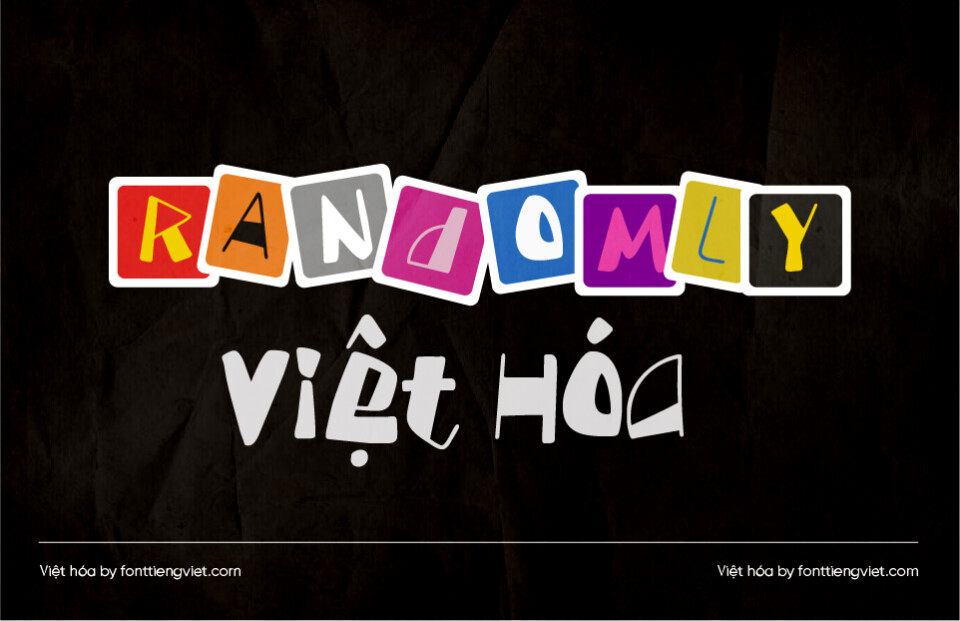
Font Việt hóa 1FTV Randomly Regular
Trong thế giới đồ họa hiện đại, việc lựa chọn một bộ Font Miễn Phí chất lượng đóng vai trò quyết định đến tính thẩm mỹ của sản phẩm. Font Việt hóa 1FTV Randomly Regular nổi lên như một giải pháp hoàn hảo cho những ai đang tìm kiếm sự phá cách và độc đáo. Đây là bộ font được tinh chỉnh kỹ lưỡng, hỗ trợ đầy đủ bộ gõ tiếng Việt, giúp người dùng dễ dàng ứng dụng vào các dự án sáng tạo mà không lo lỗi hiển thị. Với phong cách tự nhiên và ngẫu hứng, font chữ này mang lại cảm giác gần gũi nhưng không kém phần chuyên nghiệp cho mọi bản thiết kế.
Đặc điểm nổi bật của Font Việt hóa 1FTV Randomly Regular
Sự linh hoạt trong thiết kế sáng tạo
Font Việt hóa 1FTV Randomly Regular gây ấn tượng bởi những đường nét không quá gò bó, tạo nên một nhịp điệu thị giác thú vị. Các ký tự được thiết kế với độ dày vừa phải, giúp văn bản duy trì được sự rõ ràng trên cả định dạng in ấn lẫn kỹ thuật số. Điều này giúp các bạn học sinh và giáo viên dễ dàng sử dụng để làm slide bài giảng hoặc báo tường sinh động.
Khả năng tương thích và ứng dụng đa dạng
Bộ font này đặc biệt phù hợp cho các tiêu đề sách, thiệp mời, hoặc các ấn phẩm truyền thông mạng xã hội. Nhờ quy trình Việt hóa chuẩn xác, các dấu thanh được đặt vị trí hợp lý, đảm bảo sự cân đối cho đoạn văn. Người dùng có thể kết hợp font chữ này với nhiều phong cách khác nhau từ vintage cổ điển đến hiện đại tối giản.
Cách sử dụng Font Việt hóa 1FTV Randomly Regular hiệu quả
Để phát huy tối đa vẻ đẹp của bộ font, bạn nên sử dụng nó cho các đoạn văn bản ngắn hoặc tiêu đề chính để tạo điểm nhấn. Việc kết hợp cùng các tông màu pastel hoặc trung tính sẽ giúp chữ viết trở nên nổi bật hơn. Đừng quên kiểm tra khoảng cách giữa các chữ cái để đạt được hiệu quả thị giác tốt nhất cho dự án của mình.